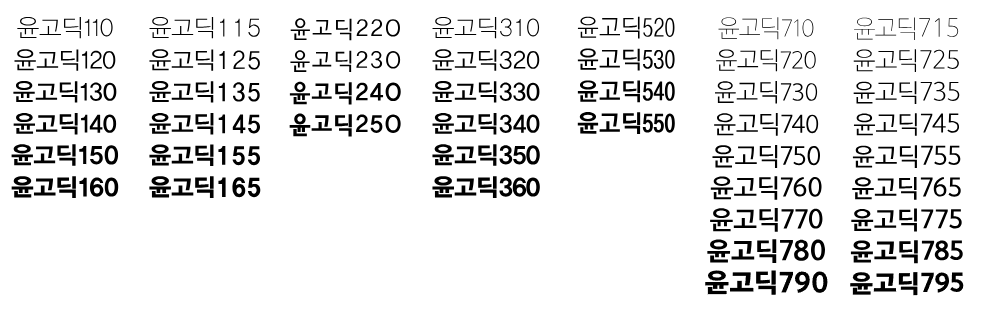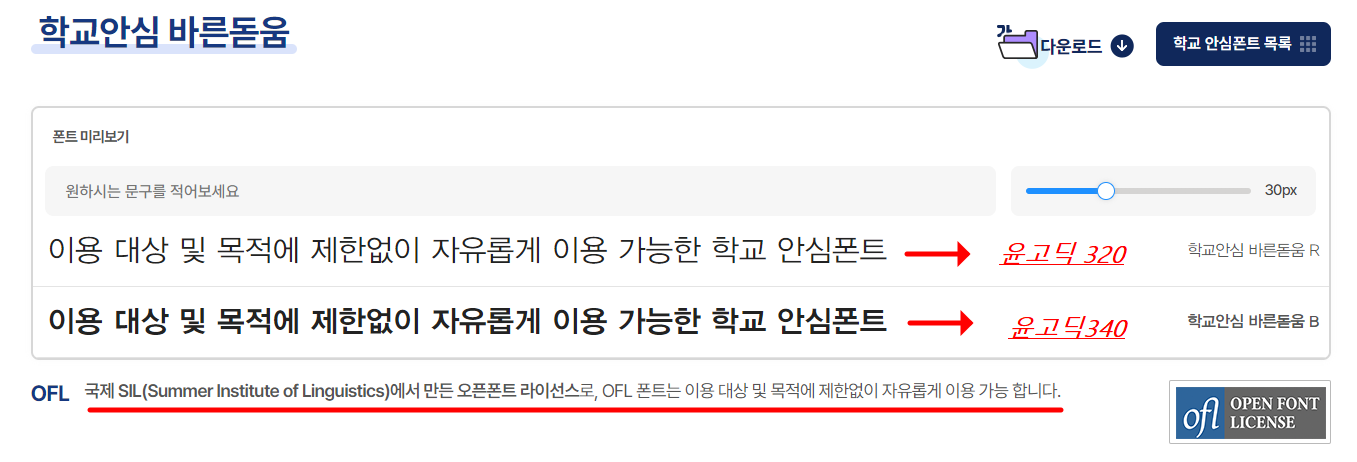
윤고딕 종류
윤고딕은 윤디자인그룹에서 개발한 폰트 종류입니다. 최근에 글꼴 사이트로 유명한 산돌구름에서 윤디자인을 인수했다는 뉴스가 확인되었어요. 어디까지 커질지 기대가 되고 있습니다.
대표적인 윤고딕 글꼴 종류는 다음과 같습니다.
- 윤고딕 300
- 윤고딕 400
- 윤고딕 500
- 윤고딕 700
이 폰트 중에서도 대중적으로 많이 사용되는 폰트는 윤고딕 300 시리즈입니다. 오늘 무료로 다운로드 가능한 폰트가 바로 윤고딕 300 시리즈 중에서 윤고딕 320과 340입니다.